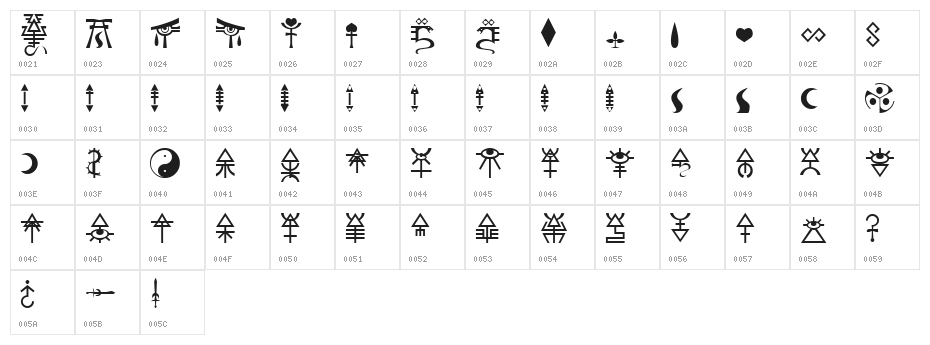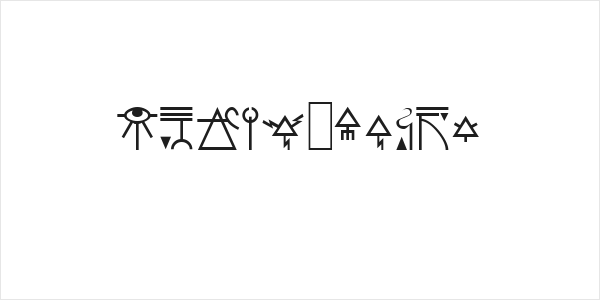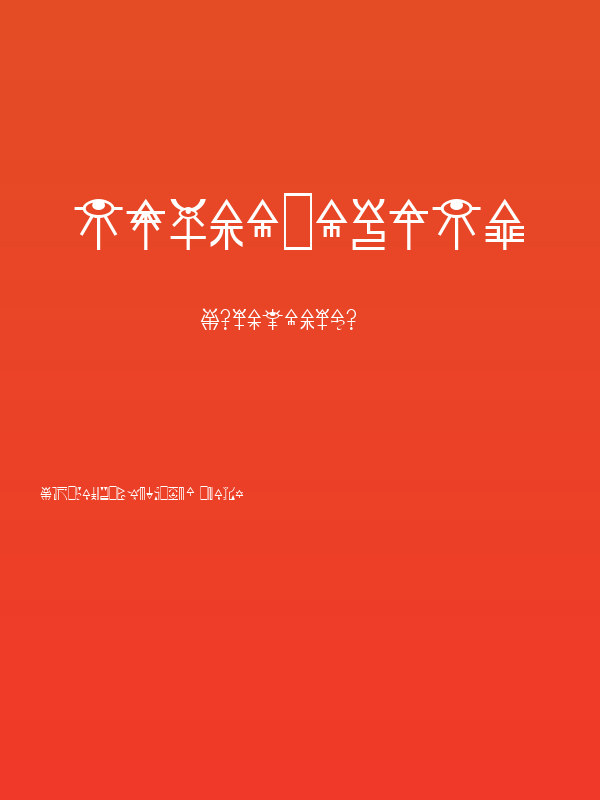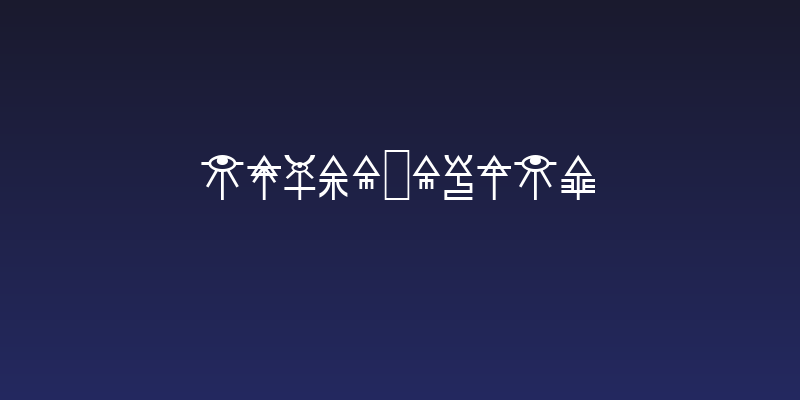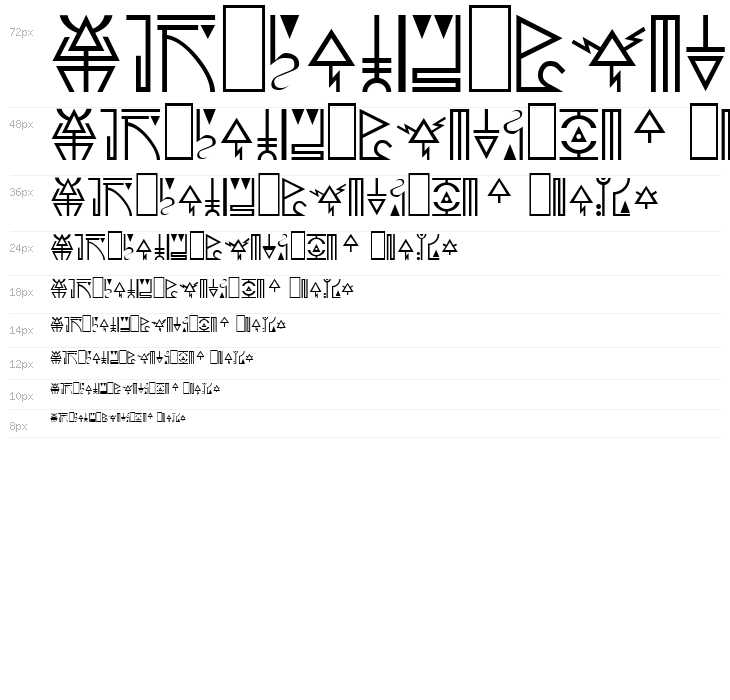
Eldar Runes Font
| Общий стиль | Mystical, Ancient, Decorative |
| Область применения | Logos, Titles, Decorative elements |
| Рекомендуемые проекты | Ideal for fantasy-themed projects, game design, book covers, or any creative work that requires an ancient or mystical aesthetic. |